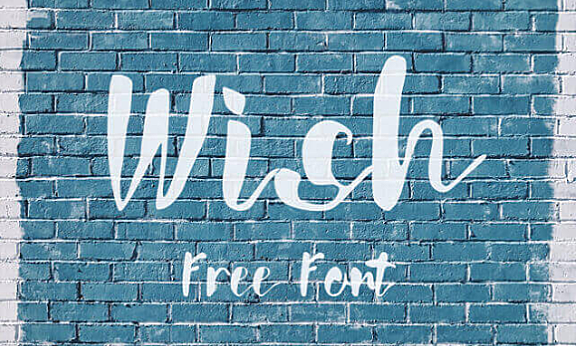
[系统字体] 美观独特的字体:wish 资源介绍参数 资源类别: 精美字体 如遇问题: 联系客服/留言反馈 下载地址: 前往下载 精美字体 21年1月19日 编辑 前往下载 喵容发布2号 取消关注 关注 私信 Wish字体具有独特有趣的波浪笔触,非常适用于品牌,标题,服装,海报,邀请函设计等等。 相关文章: [系统字体] 复古脚本字体:本文介绍的是一款具有复古外观的脚本字体——Buffalo。它是品牌和标志设计的理想选择,有需要的朋友可以到文末下载哦! 下载权限查看 ¥ 免费下载 评论并刷新后下载 登录后下载 查看演示 {{attr.name}}: 您 …... [系统字体] 一款灵感来自动物的字体:本文分享的一款字体(faune)。这款字体是由Alice Savoie在国家艺术中心与Groupe Imprimerie Nationale合作委托的背景下创建的的。该字体灵感来源于动物,并以两部伟大的历史作品为基础。可以说是一款具有 …... [系统字体] 一款装饰性极强的字体——Moalang:今天分享的是一款装饰性非常强的一款字体——Moalang。它由印度尼西亚的字体设计师Agga Swist’blnk设计并且免费用于个人和商业用途! 喵容——Moalang字体1喵容——Moalang字体2 下载权限查看 ¥ 免费下载 …... [系统字体] 分层复古字体 BERG字体:资源名称 BERG 资源大小 244mb 资源格式 ttf、png 资源简介 Berg包含一整套大写和小写字母,以及多语言支持,货币数字,数字和标点符号。 喵容——BEGR字体1喵容——BEGR字体2 下载权限查看 ¥ 免费下载 评论并 …... [系统字体]优雅现代手写英文字体 Domillion字体:资源名称 Domillion 资源大小 591kb 资源格式 ttf、otf 资源简介 Domillion是海报,签名,标识,报价,专辑封面,名片,产品设计等的完美选择!该字体免费供个人使用! 喵容——Domillion-Brush-Font1喵容——D …... [系统字体]优质的装饰字体——Sabrva:资源描述 字体 资源名称 Sabrva 资源格式 ttf 资源大小 7.35kb 资源简介 Sabrva是完美字体的选择,可在 – 水印,签名,摄影,徽标,名片,报价,专辑封面使用。免费供个人使用! 喵容——Sabrva1喵容—— …... 喵容——wish字体1喵容——wish字体2 下载权限查看 ¥ 免费下载 评论并刷新后下载 登录后下载 查看演示 {{attr.name}}: 您当前的等级为 登录后免费下载登录 小黑屋反思中,不准下载! 评论后刷新页面下载评论 支付¥以后下载 请先登录 您今天的下载次数(次)用完了,请明天再来 支付积分以后下载立即支付 支付以后下载立即支付 您当前的用户组不允许下载升级会员 您已获得下载权限 您可以每天下载资源次,今日剩余次 声明:本文为原创作品,版权归作者所有。未经许可,不得转载或用于任何商业用途。如若本站内容侵犯了原著者的合法权益,可联系我们进行处理。 给TA打赏 共{{data.count}}人 人已打赏 wish字体下载波浪